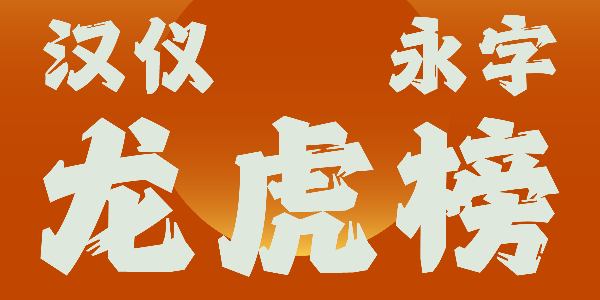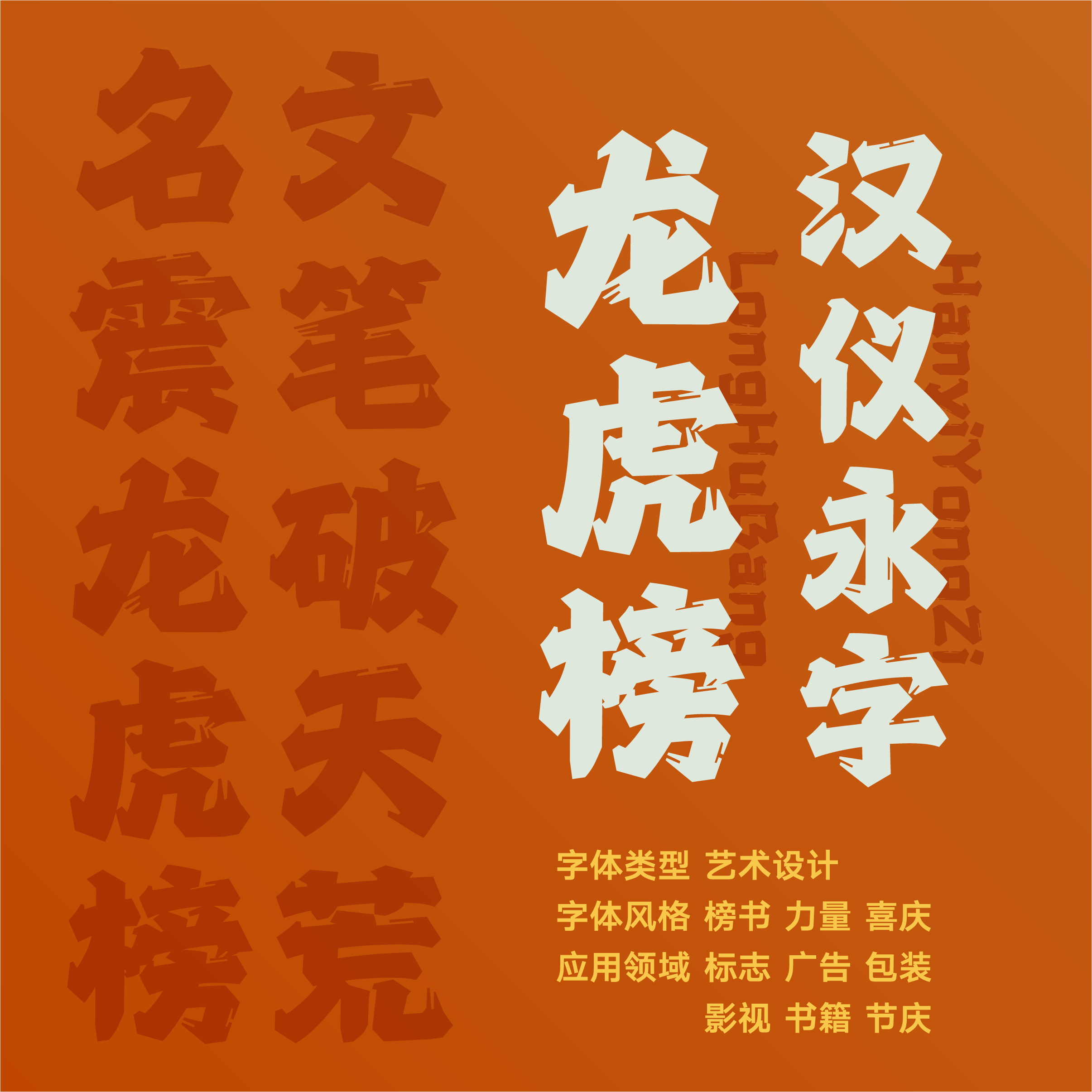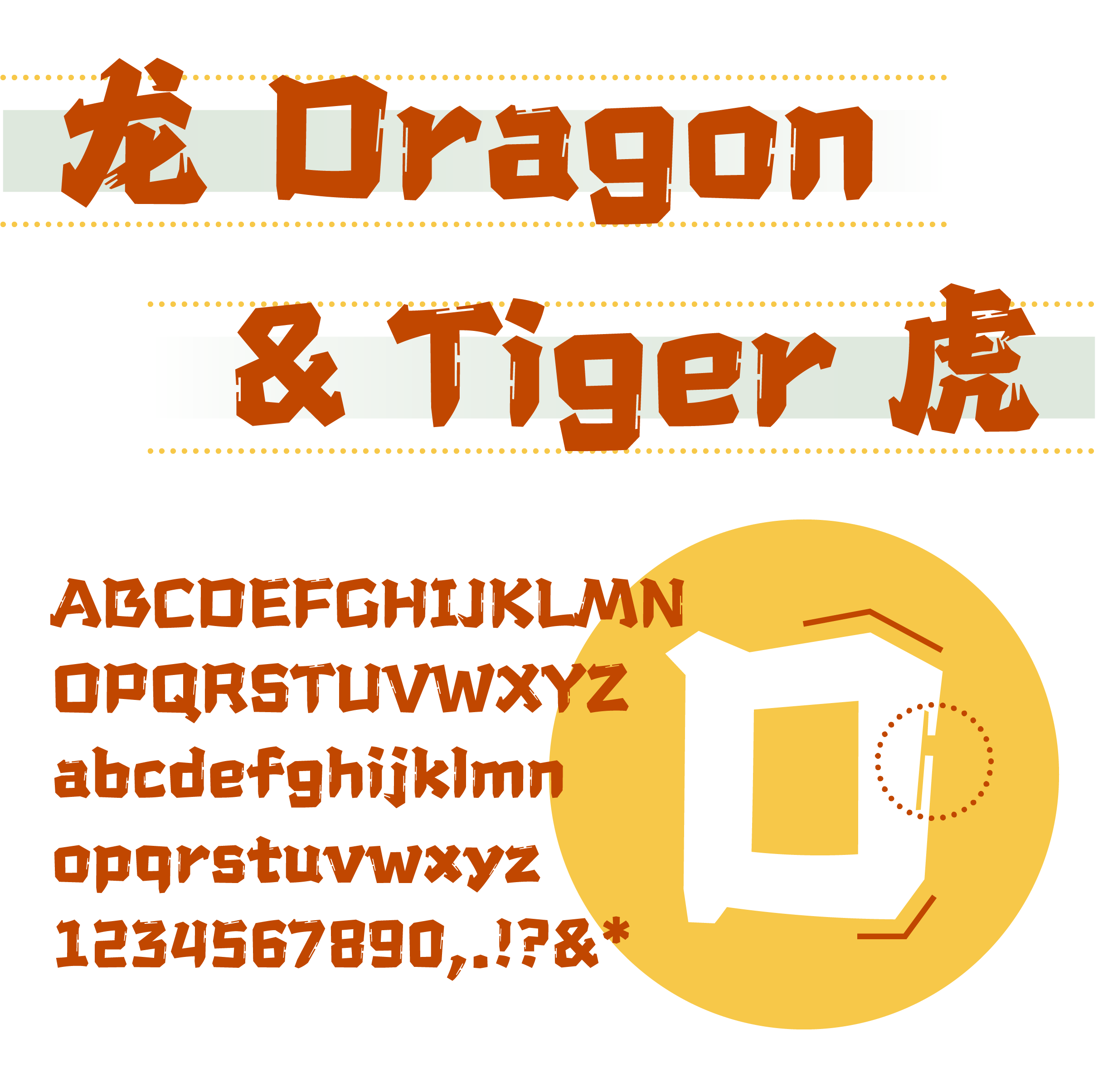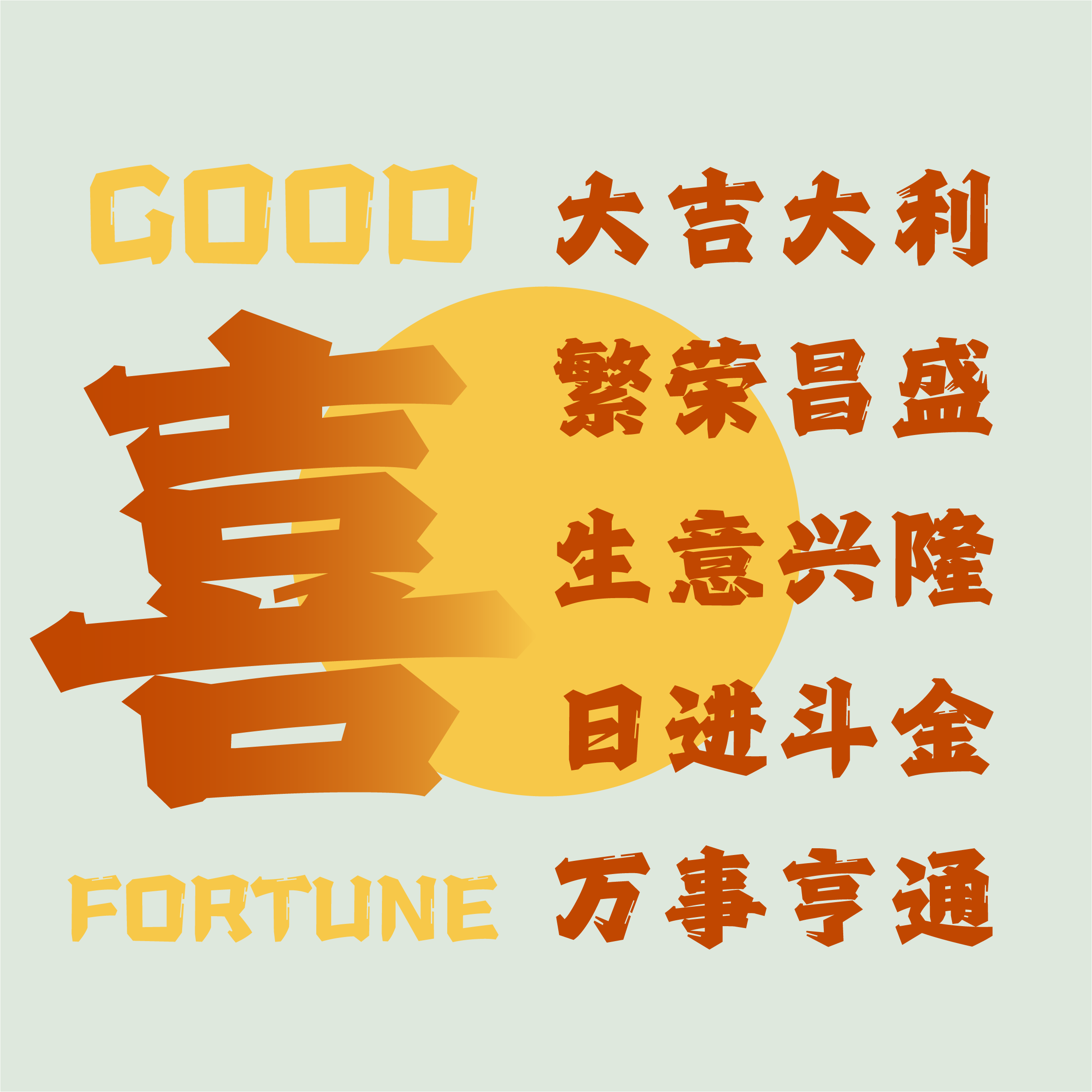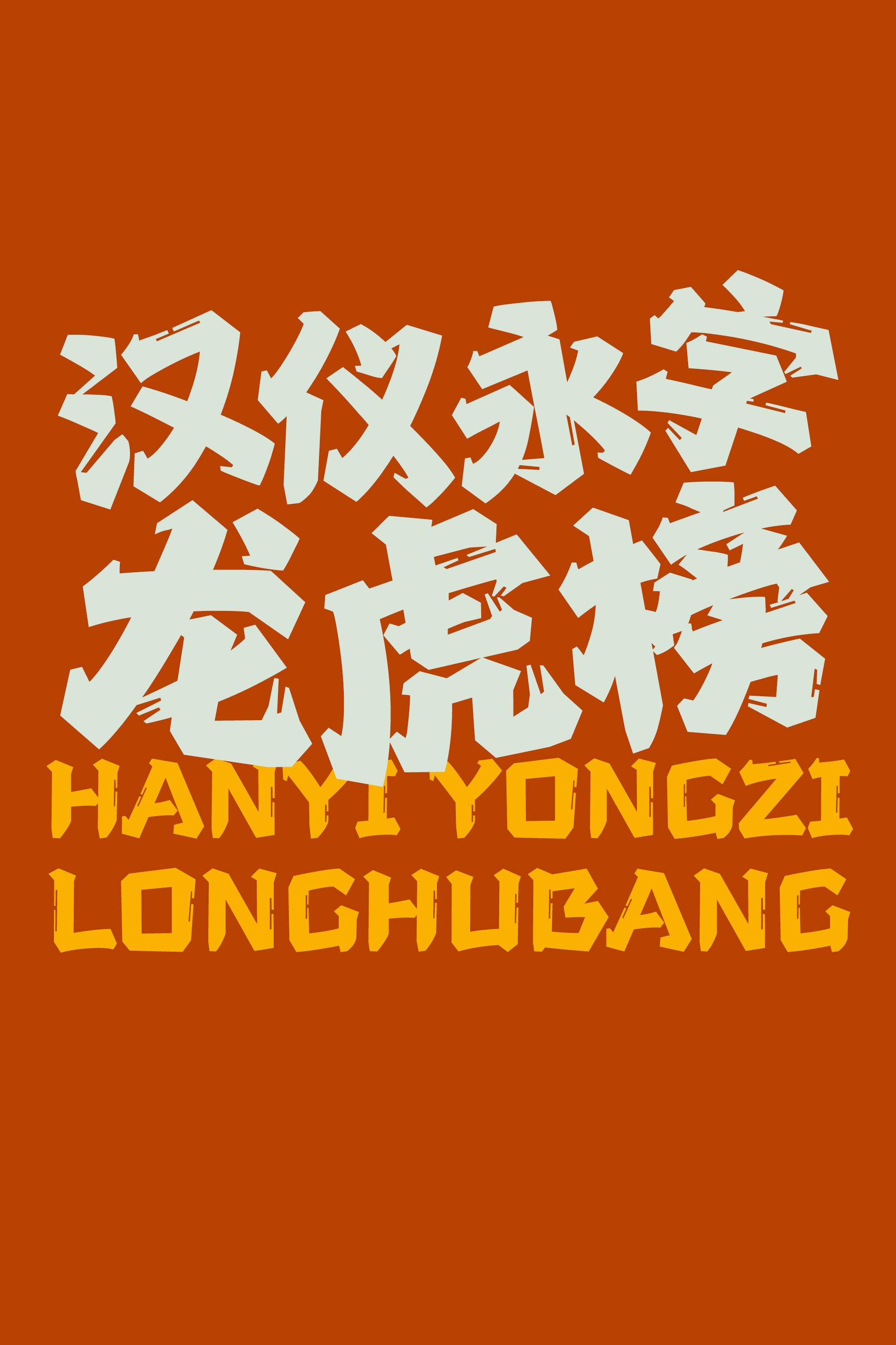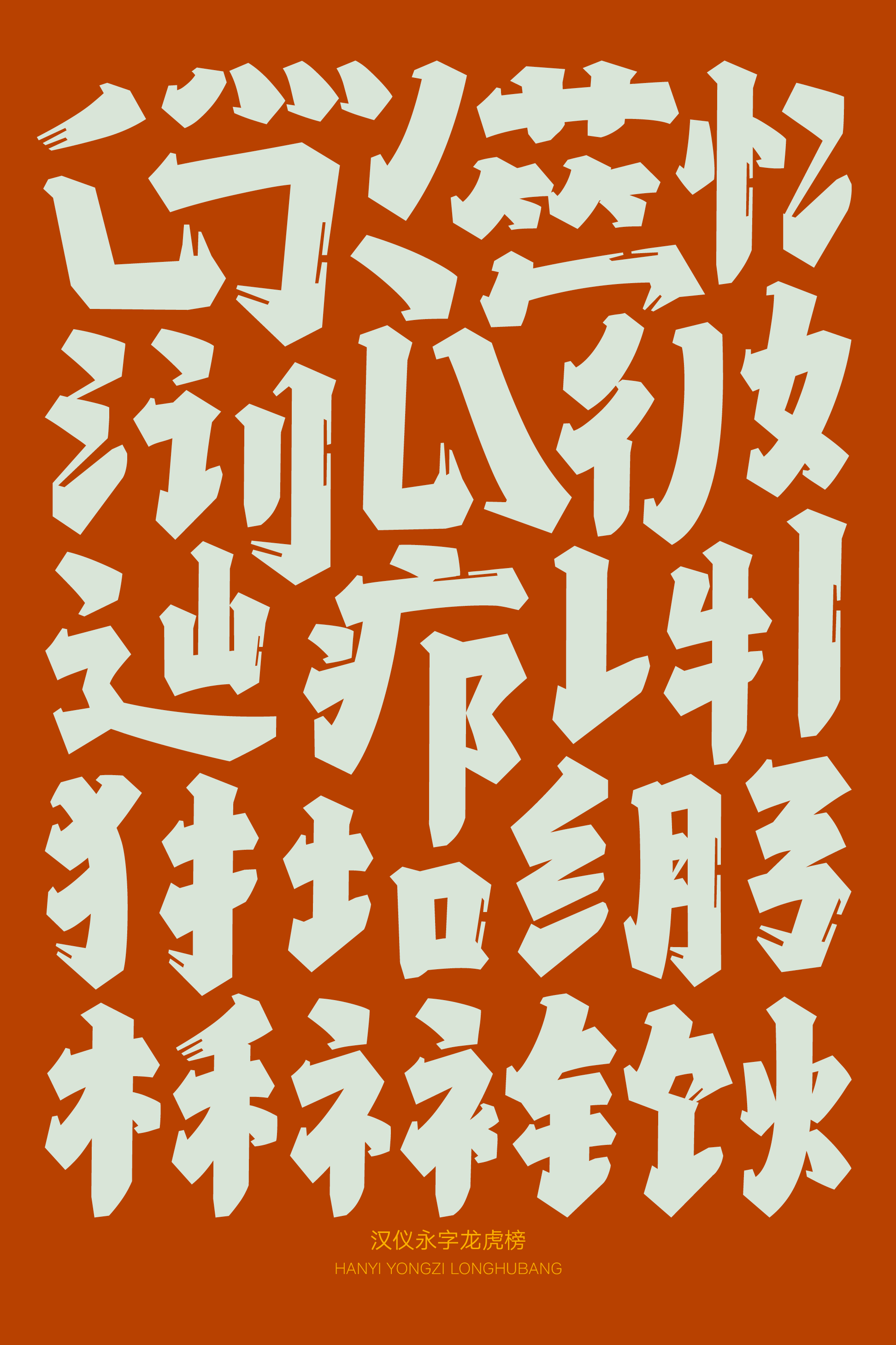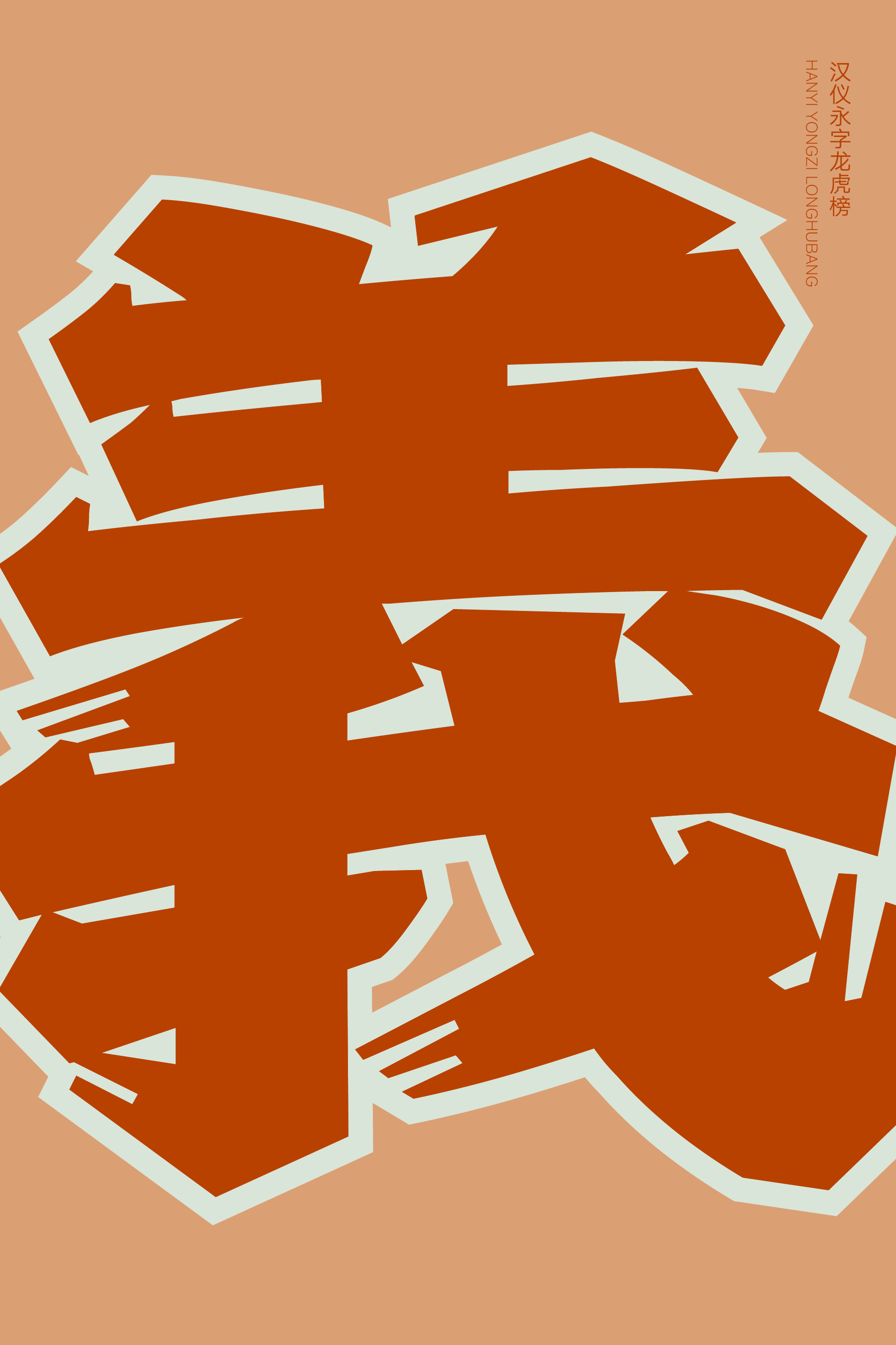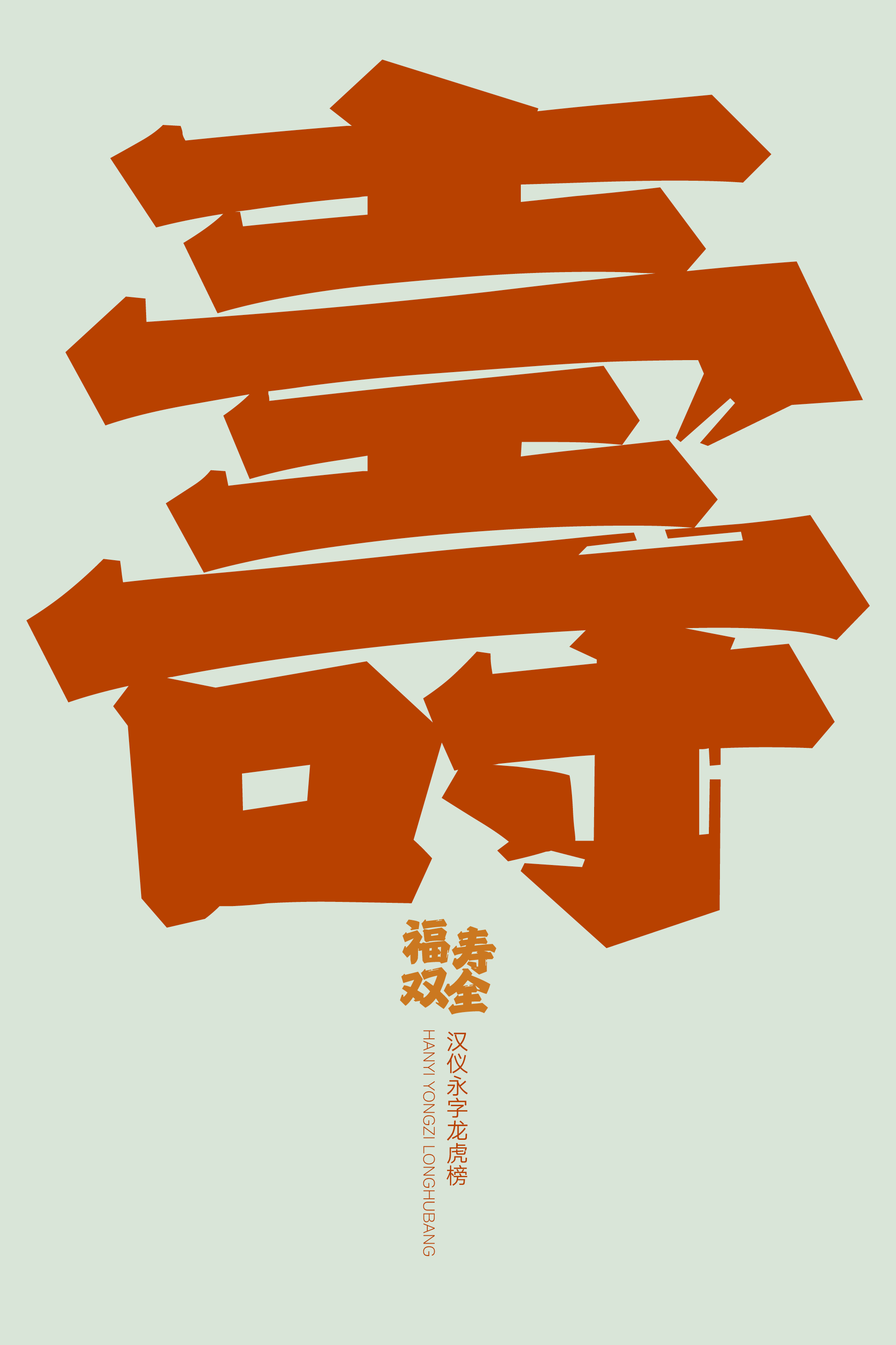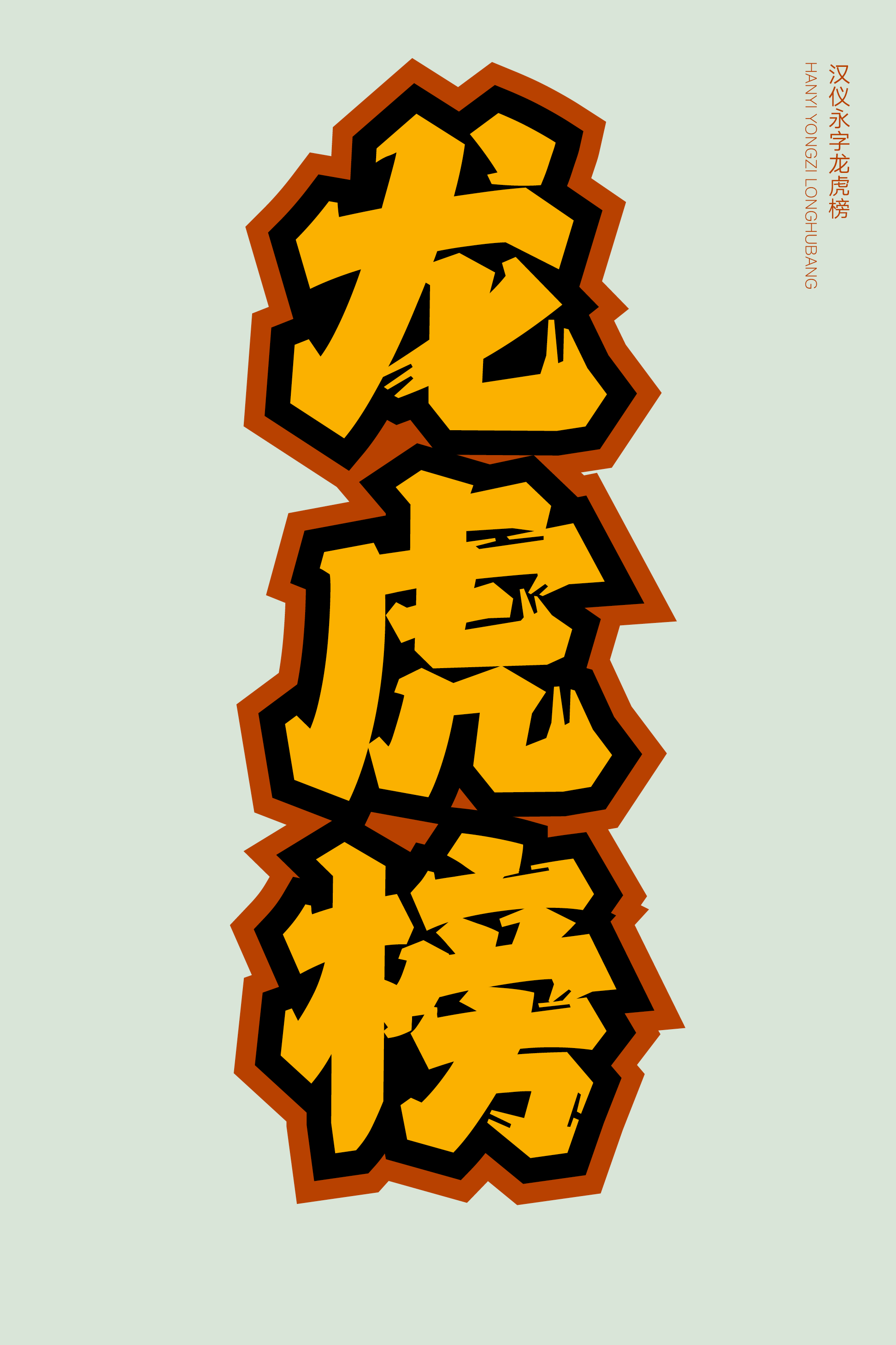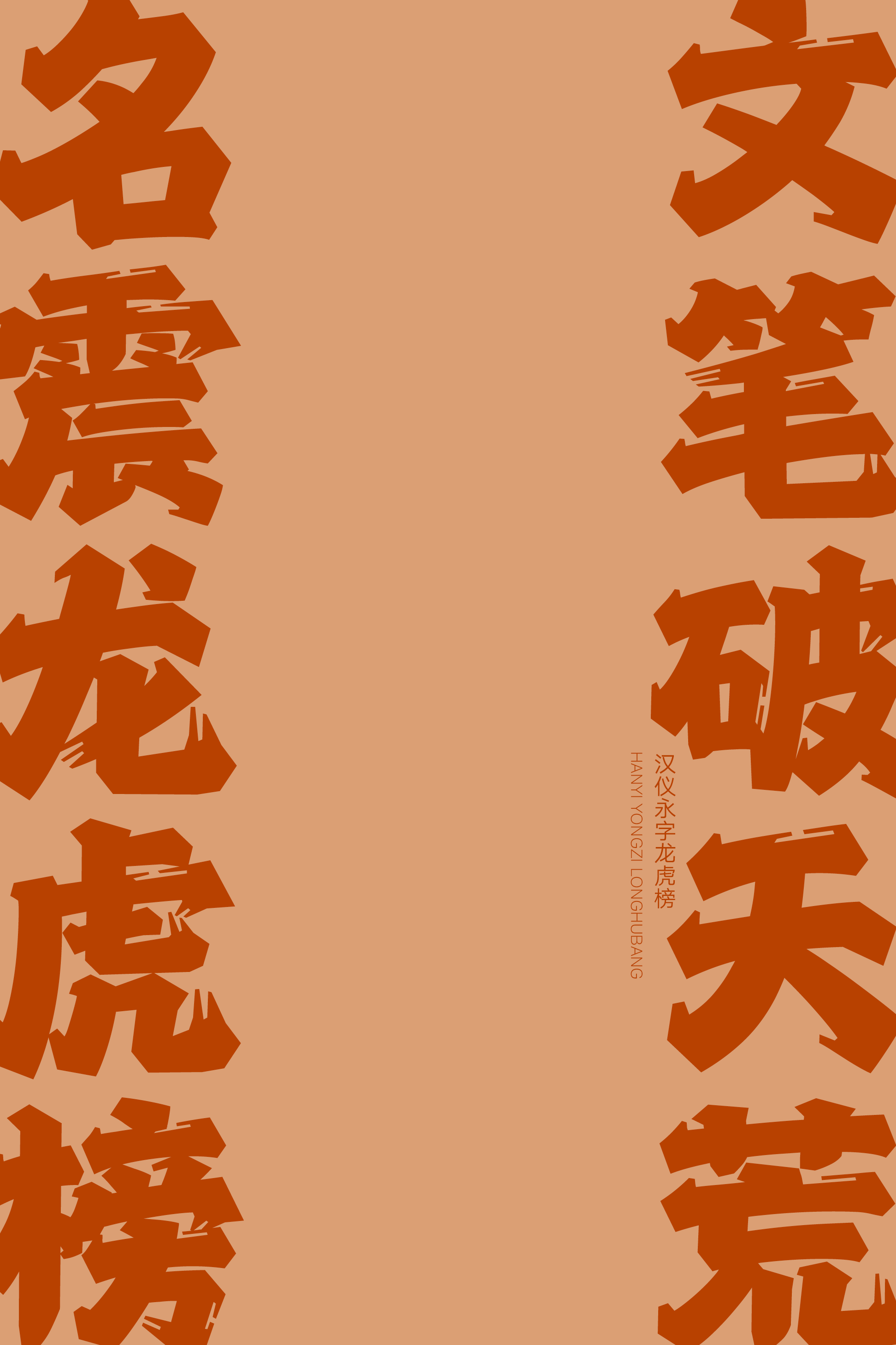
汉仪永字龙虎榜
汉仪永字龙虎榜,由永字社创作,“字”说吉祥,是一款喜庆欢腾的榜书风格标题字体。字形端正,笔画粗重,抑扬顿挫、潇洒自如,点缀以传统舞龙舞狮似的流苏装饰,整体恢宏大气、欢喜热闹,适合用于传统节庆、联欢晚会、电商活动等使用场景。
字形方而端正,略有斜势,承袭榜书恢弘的气势。
笔画设计带有书写的抑扬顿挫,间以牵丝和连带。
点缀以装饰元素,似传统舞龙舞狮的流苏。
西文部分造型为方,线条化曲为直,点缀以流苏装饰元素,中西文视觉语言统一。
“字”说吉祥,这款喜庆欢腾的榜书风格标题字体适合用于传统节庆、联欢晚会、电商活动等使用场景,渲染一抹浓郁的喜悦。